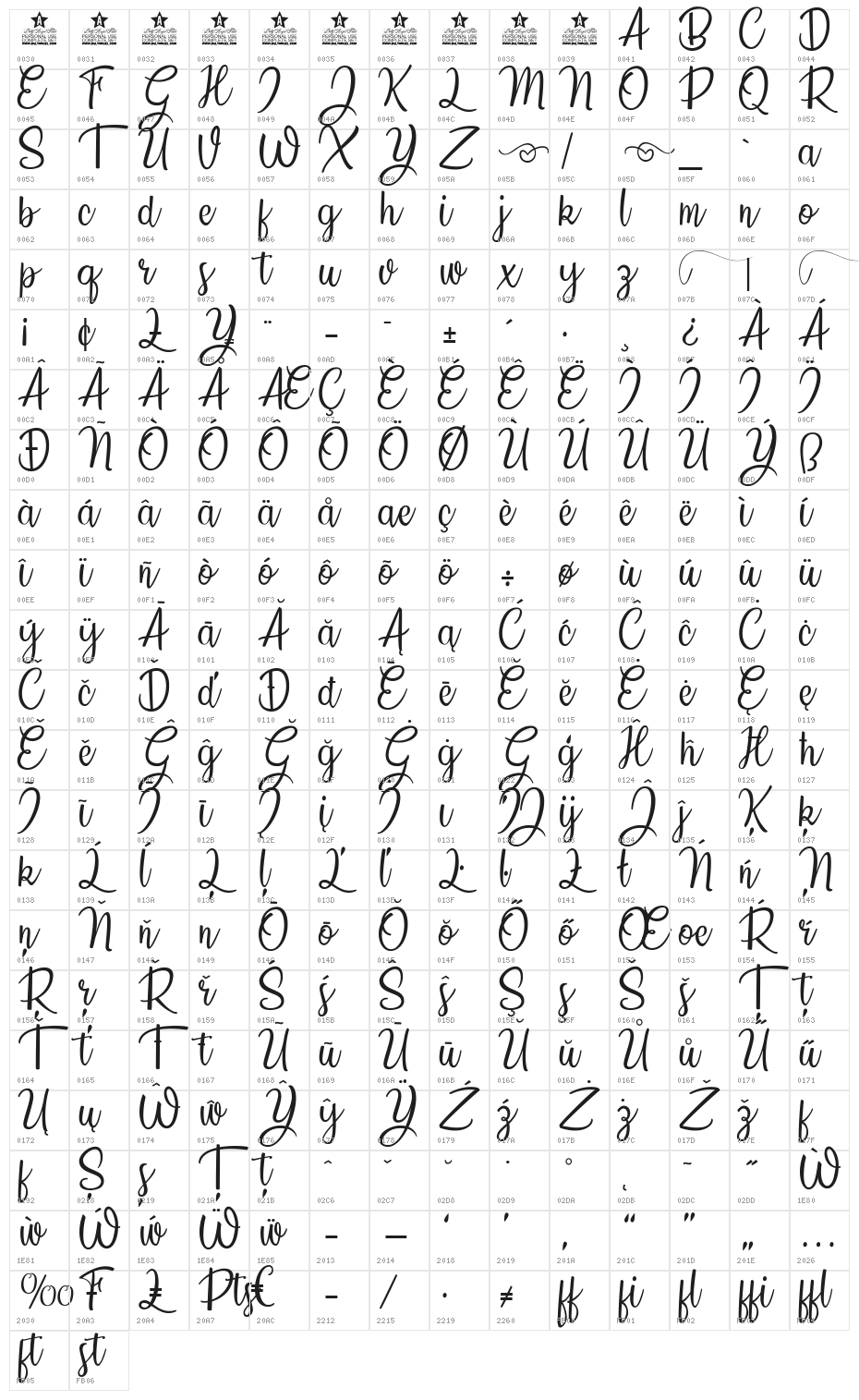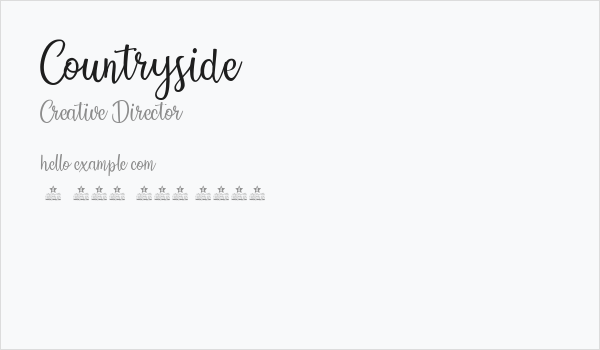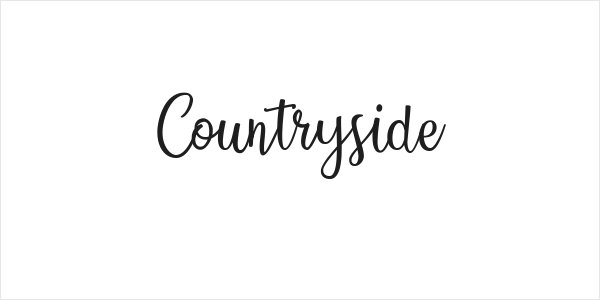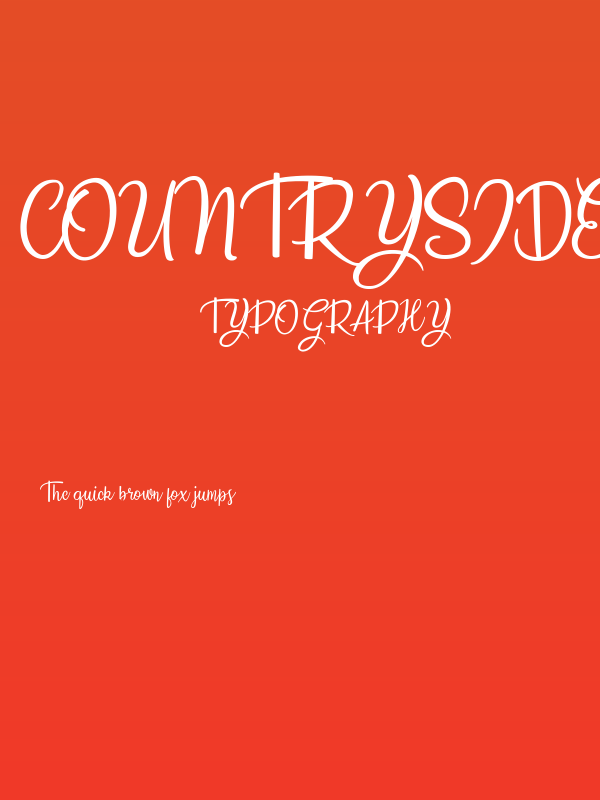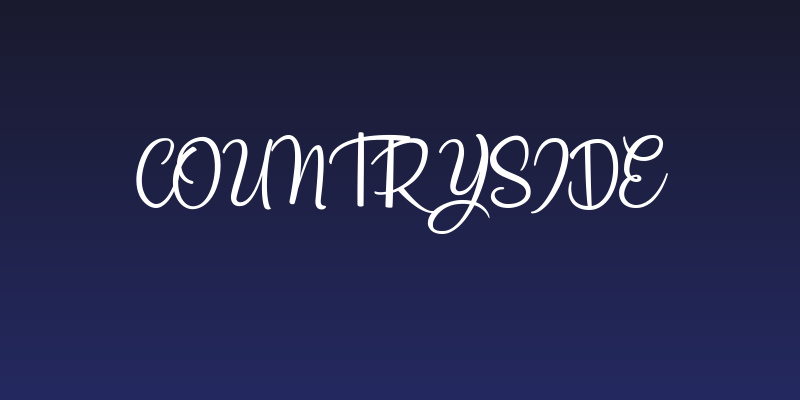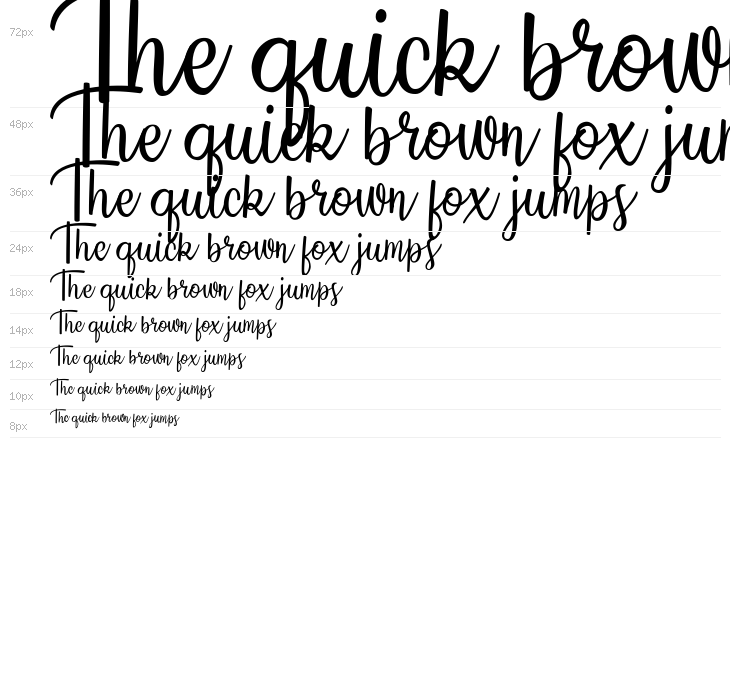
Countryside Font
✎ Script
| Gesamtstil | Elegant, Classic |
| Anwendungsfall | Logos, Invitations, Decorative text |
| Vorgeschlagene Projekte | Ideal for wedding invitations, greeting cards, branding, and elegant packaging designs. |